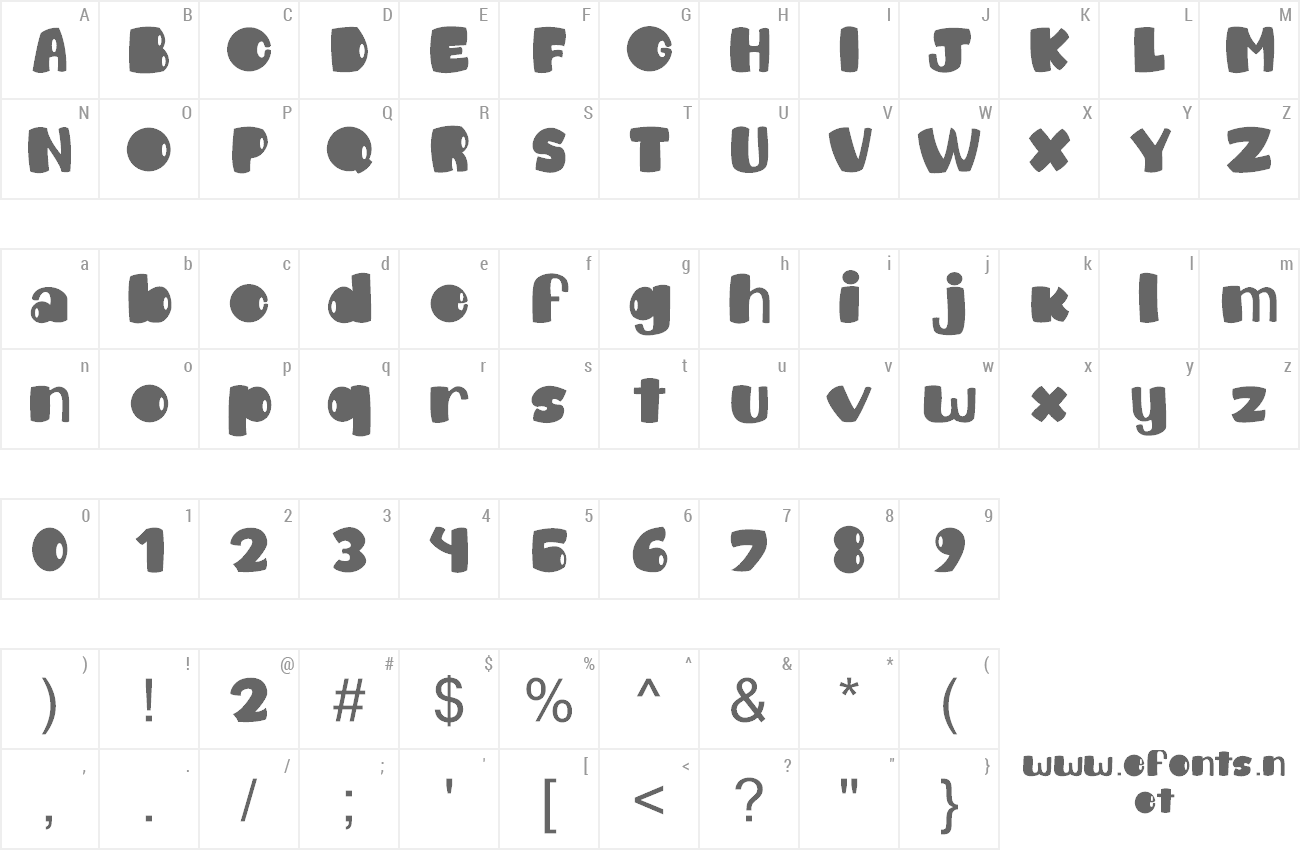
Preview and download Chico Font. Created by YolandaBomfim in Fancy Cartoon styles with 100% Free license.
| Font name: | Chico |
| Author: | YolandaBomfim |
| Note by YolandaBomfim | |
| Trabalho final para disciplina de Tipografia Digital inspirado em tipografias da década de 80. Vide Fresh Prince. |